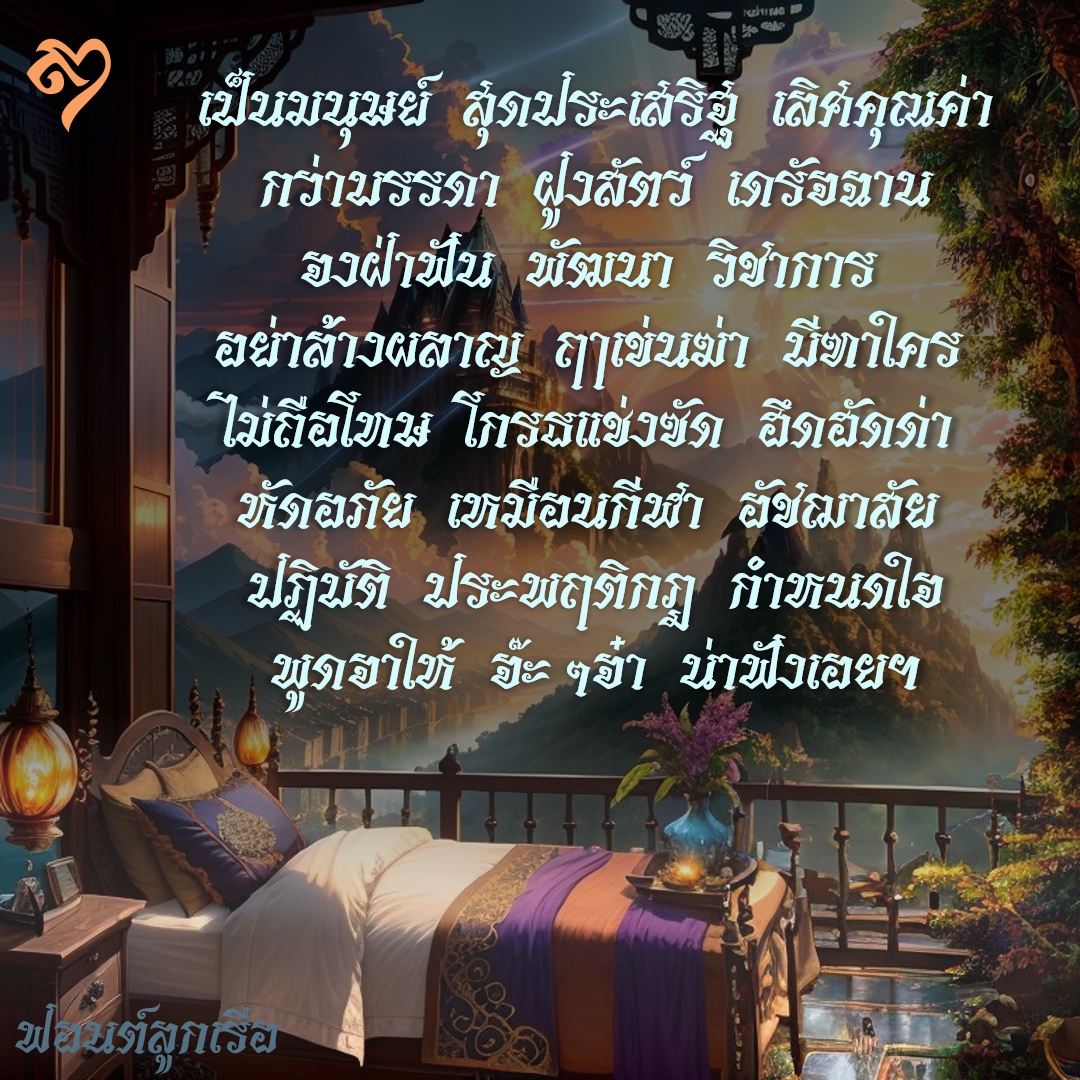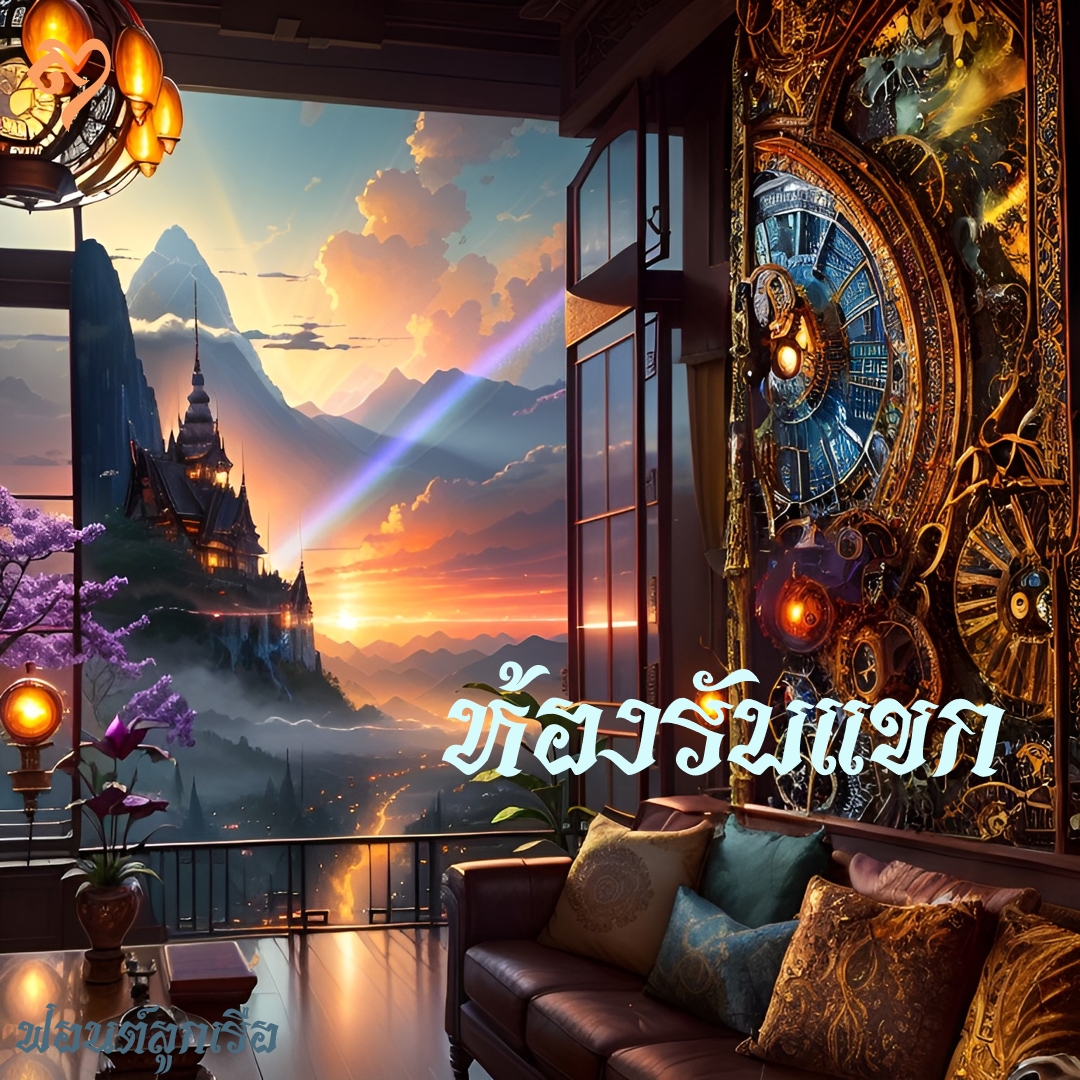
ฟอนต์ ลูกเรือ
ฟอนต์ลูกเรือ แนวทางจากอักษรไทย่อ ลดความกว้างและองศาเอียงลงเพื่อลดเนื้อที่ ตอนแรกทำมาผอมๆ แต่พอพิมพ์ดูแล้วมันอึดอัดมากไปเลยต้องขยายพื้นที่หายใจให้หลายๆตัวอักษร หน้าตาก็เลยกลับมาคล้ายๆฟอนต์ที่มีกันอยู่แล้ว..ปั๊ดโธ่
ใช้พาดหัว ข้อความสั้น ตัวเล็กไม่เหมาะเท่าไร
ฟอนต์ลูกเรือ แนวทางจากอักษรไทย่อ เหมาะพาดหัว ข้อความสั้น
สะบัดสนุกมากครับ